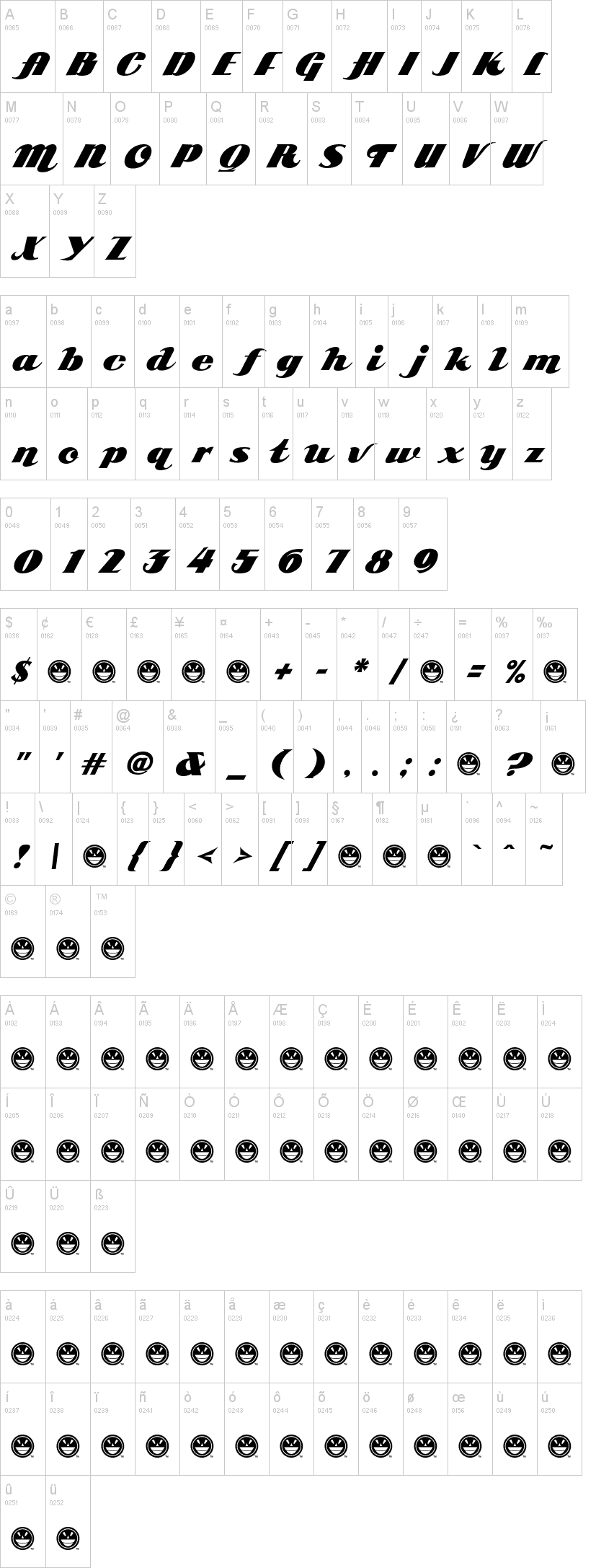
ARB 85 Poster Script JAN-39 字体是一种基于手写字体的艺术字体,由托尼·弗里斯创作。该字体具有大写字母、数字和一些标点符号,它的设计灵感来源于20世纪三十年代的美国传单和海报。 该字体的特点是线条粗细不一,笔画有强烈的艺术感,字母之间的间距也较大,使得整个字体看起来很有力量和震撼力。该字体适合用作海报、标志、广告和其他需要吸引注意力的设计项目。 该字体支持多种语言,包括英语、西班牙语、法语、德语等,可以在许多不同的设计项目中使用。此外,该字体还提供了一些额外的特殊字符,如箭头和星号等,可以增加设计的多样性和创意性。 总的来说,ARB 85 Poster Script JAN-39 字体是一种非常适合需要强烈表现力的设计项目的艺术字体,它的设计风格简洁明了、时尚独特,可以给设计师带来很多的灵感和创意。内容介绍
ARB 85 Poster Script JAN-39是一款非常不错的手写艺术字体,具有很好的视觉感,适合于文化类的宣传设计、商业类品牌的广告和产品包装设计以及个性化文字排版等较多场景。